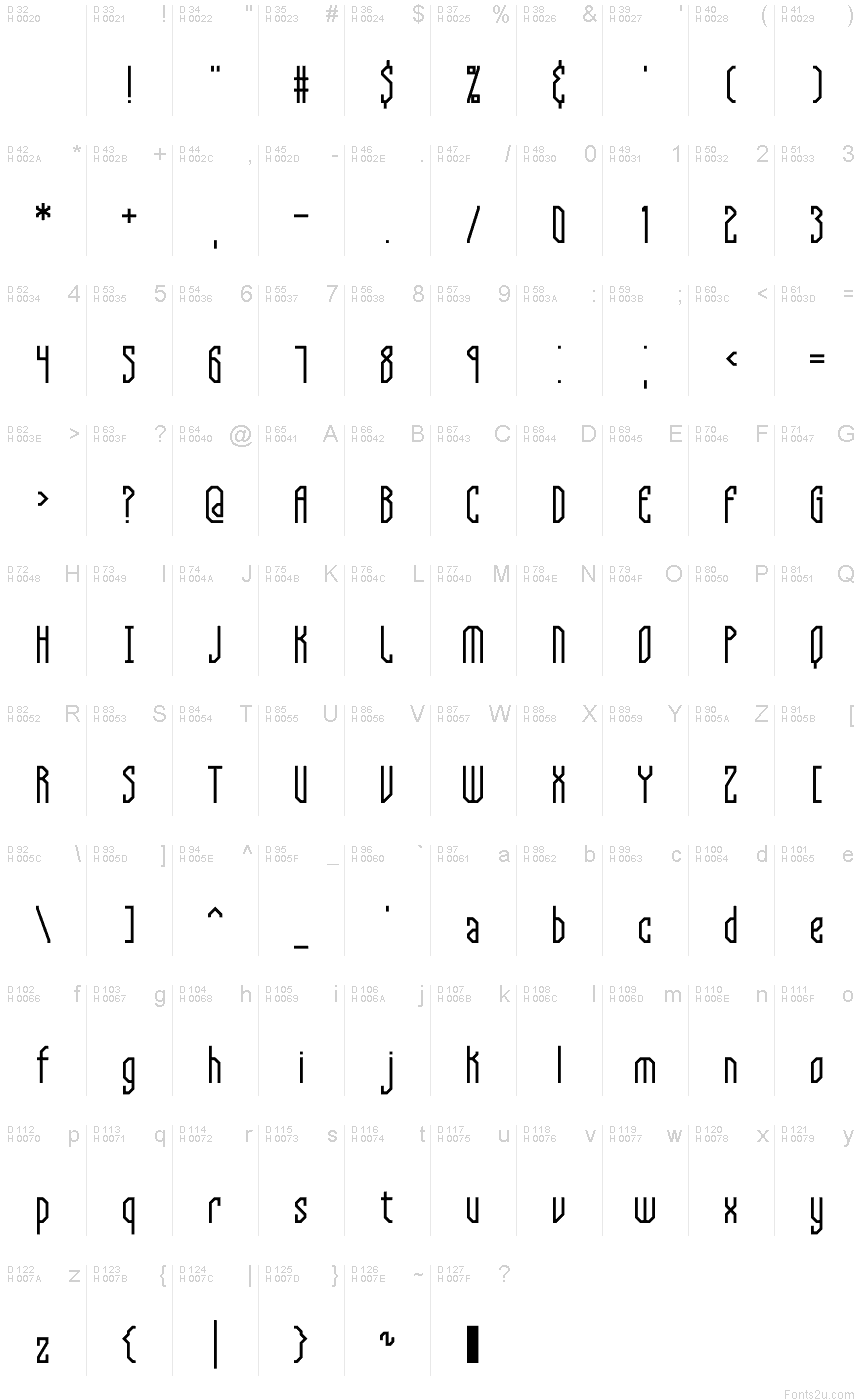
Supra Genius Lines BRK
Supra Genius Lines di ÆNIGMA Fonts è un font display techno gratuito, caratterizzato da un ritmo slanciato e angolare e da un aspetto schematico che ricorda i circuiti. Le lettere sono costruite con tratti sottili e angoli smussati, conferendo al font l'aspetto di una segnaletica futuristica tracciata in un unico gesto continuo, anziché quello di un classico stile display pesante e squadrato.
Si adatta perfettamente a poster sci-fi, loghi di videogiochi, flyer per club, copertine di album e titoli dove le parole brevi necessitano di un tocco elettronico incisivo. Come font gratuito, è ideale anche per il branding ispirato alle interfacce, la grafica per lo streaming e i monogrammi essenziali, soprattutto quando si vuole che le lunghe linee verticali e gli incastri geometrici creino il massimo impatto visivo.